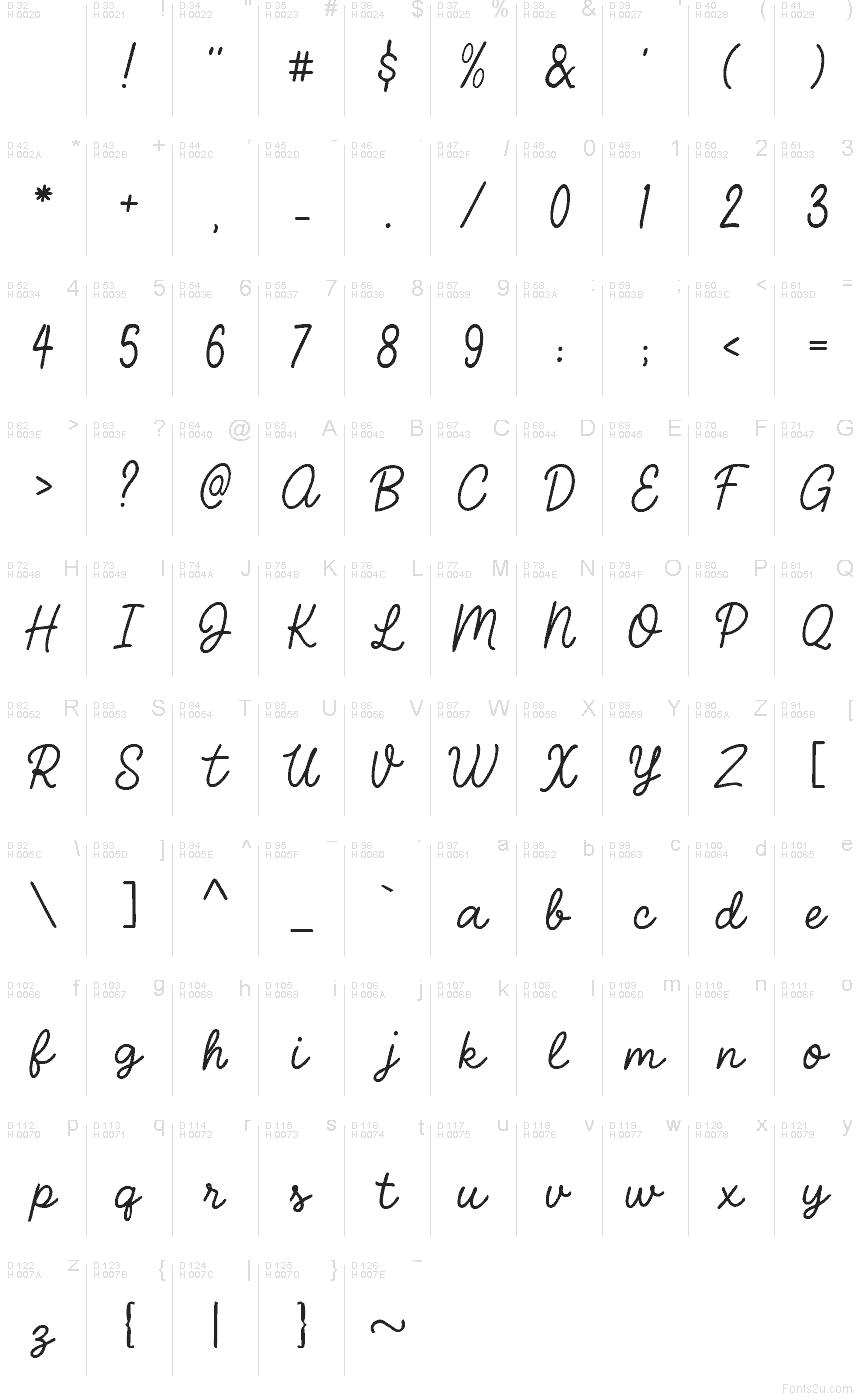
Le Jardin Secret, da BlackFridayFont, é uma fonte script romântica gratuita que traz o clima arejado e sinuoso das placas francesas e das anotações em cafés. As letras apoiam-se em curvas longas e elásticas e em junções arredondadas, com grandes swashes de entrada e curvas suaves que tornam o visual leve, fluido e um tanto sedutor.
É perfeita para branding de boutiques, papelaria de casamento, embalagens de cosméticos, capas de revistas e títulos curtos de restaurantes onde se busca uma fonte gratuita que transmita calor em vez de formalidade. Use também em logotipos, cartões de apresentação ou iniciais estilo monograma — as aberturas amplas e as alças altas dão espaço para que palavras curtas respirem.